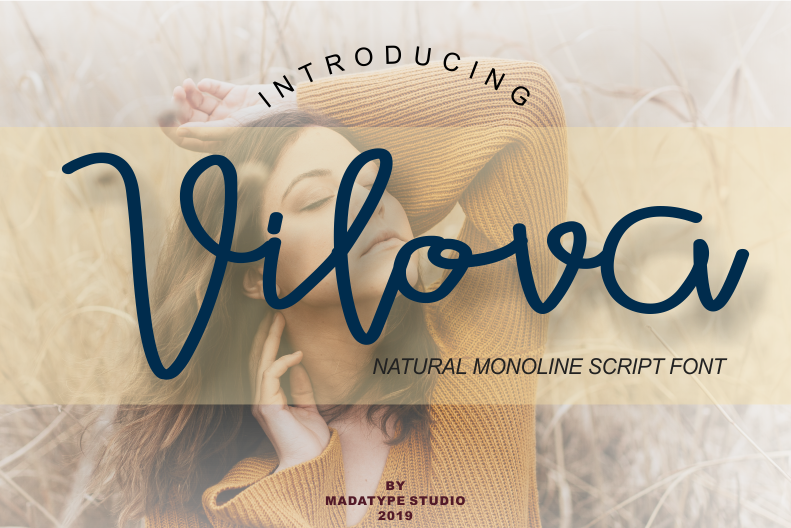
Vilova Script Font – Download Grátis
A Vilova é uma fonte escrita à mão monoline que transforma seus designs em resultados chamativos. Se você precisa de uma licença adicional para fins comerciais, não hesite em entrar em contato conosco. A Madatype Studio nos apresenta Vilova Script Font, uma fonte única e elegante perfeita para criar uma assinatura personalizada marcante. Experimente mais produtos da nossa loja. Vamos transformar seus projetos de design em algo excepcional com Vilova.
Designer: Madatype Studio